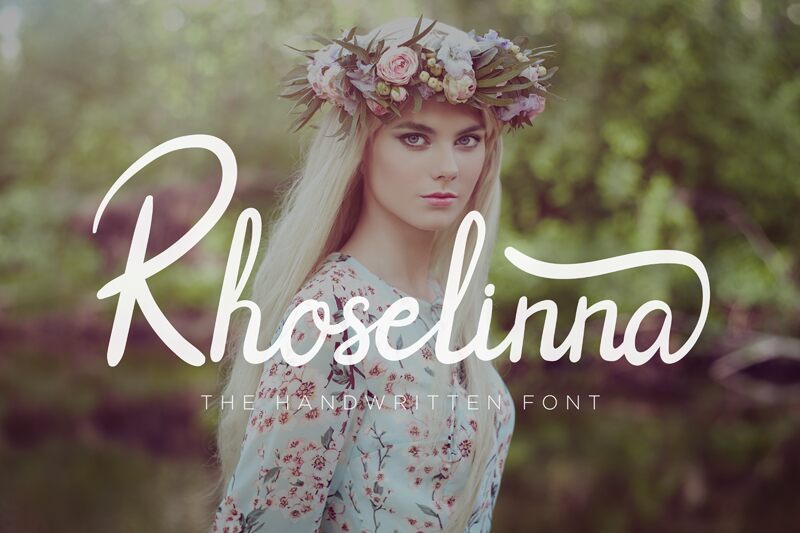
隆重推荐 RHOSELINNA !!!
Rhoselinna 是一款手写风格字体,非常适合用于标志设计、品牌推广、家居装饰、产品包装、马克杯、引用语、海报、购物袋、T恤、书封、名片、邀请函、贺卡、标签、摄影、水印、特殊活动以及所有其他需要手写质感的迷人项目。
Rhoselinna 字体特点:
- 完整的大小写字母集
- 标点符号与数字
- 连字及可选样式集 (Stylistic Set)
- 多语言支持